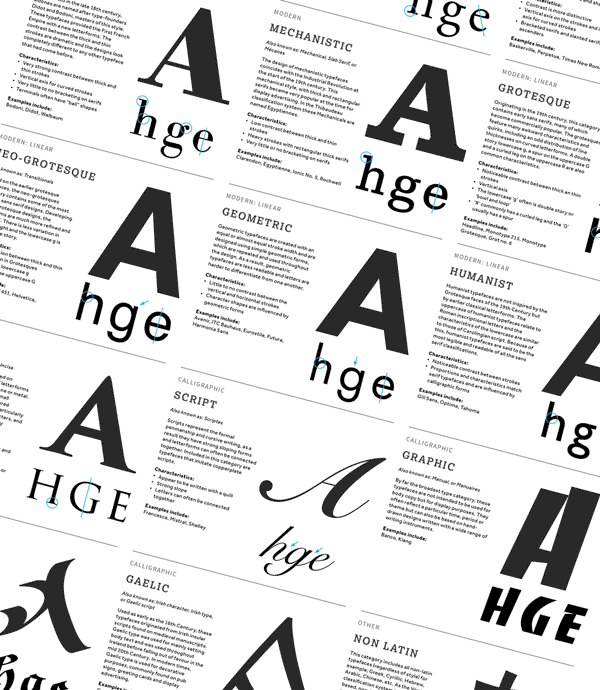
la classification Vox/AtypI
La classification Vox/AtypI inventée par Maximilien Vox en 1954, a été adoptée en 1962 par l’Association Typographique Internationale (ATypI). Cette classification possède également la caractéristique d’avoir été traduite en anglais et en allemand, renforçant ainsi son caractère universel.
Cette classification distingue 4 groupes de familles :
I – Les classiques: Humanes, Garaldes et Réales
Le groupe des Humanes, Garaldes et Réales constitue la trilogie des caractères classiques ou historiques.
II – Les modernes: Didones, Mécanes et Linéales
Le groupe des Didones, Mécanes et Linéales constitue la trilogie des caractères modernes, nés avec la Révolution industrielle vers la fin du XIXe siècle. Sous l’influence du machinisme, ces caractères ont pour particularité d’être constitués de traits simples et fonctionnels.
III – Les calligraphiques: Incises, Scriptes, Manuaires, Fractures
Le groupe des Incises, Scriptes et Manuaires constitue la trilogie des caractères d’inspiration calligraphique.
IV – Les non latines ou orientales
Les non-Latines regroupent les familles parfaitement hétérogènes. La famille des caractères non-latins regroupe les versions typographiées des grandes écritures qui ne sont pas basées sur l’alphabet latin. (Caractères Arabes, Chinois …)
Symbolique en quelques mots : exotiques, renvoient à une culture précise.